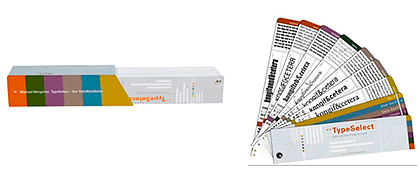
Tiens ça fait longtemps que j’ai pas été faire un tour au milieu des rayonnages d’Artazart . Je reçois cette news. Un Color Finder pour la typo, plutôt malin. Ça nous rappelle les spécimens de caractères d’il y plus de 20 ans. Pratique sans doute. Certainement pas exhaustif. Et à en voir la photo, m’étonnerait beaucoup que les typos soient classées par familles. Mais c’est à voir et découvrir. Allez, y a du soleil sur le canal… m’y arrête avant d’aller à la conf. de Michel .